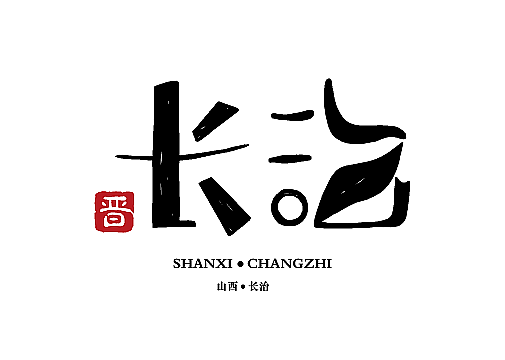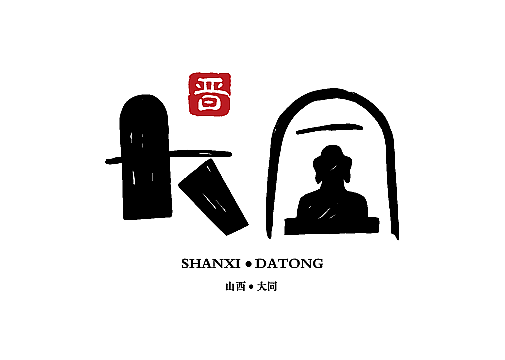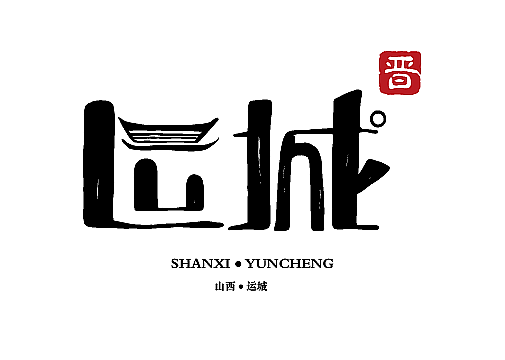
山西地名字体设计
山西是中华民族发祥地之一,有几千年的历史,具有“中国古代文化博物馆”之称。山西是一个典型的被黄土覆盖山比较多的高原,是具有许多古迹比较完整的古老遗址的旅游胜地。而我对山西11个市的市名进行字体设计,采用当地特色、旅游胜地及其建筑特征,对字体进行统一变形处理~
大同云冈石窟是世界文化遗产、国家5A级景区、首批全国重点文物保护单位。云冈石窟是世界闻名的石雕艺术宝库之一,是中国最大规模的石窟群~
阳泉-藏山风景是中华沧桑变迁的一幅重彩画卷,风景优美,历史氛围浓厚~
晋城,古称建兴、泽州、泽州府,自古为兵家必争之地,素有“河东屏翰、中原咽喉、三晋门户”的美誉~
我们或许对朔州不太熟悉,但是肯定听过走西口,而这个西口就是山西省朔州市杀虎口,而朔州最有名的是我国现存最高最完整的木塔——应县木塔~
长治,古称上党,上党梆子,山西省地方传统戏剧,国家级非物质文化遗产之一,所以我用脸谱的神韵与字体相结合,让整个字更像一个舞动水袖的花旦~
说到太原,不得不提的是太原晋祠,晋祠最为值得一看的便是雕塑、壁画、碑刻艺术,而它的建筑风格也令人耳目一新~
晋中相对于其他市而言,更像是一个古老建筑群体,其中比较有名的有榆次老城,乔家大院,平遥古城~
运城有很多景点,但被大家所熟知的当属鹳雀楼,鹳雀楼是现存最大的仿唐建筑,楼体壮观,结构奇巧,加之周围风景秀丽,唐宋之际文人学士登楼赏景留下许多不朽诗篇,以王之涣《登鹳雀楼》最富盛名~
忻州具有“旅游示范城市”之称,是修身养性的旅游胜地,而最为著名的是五台山~
临汾市历史悠久,是华夏民族的重要发祥地之一和黄河文明的摇篮,有“华夏第一都”之称~也是盛产汾酒的地方,是当地特色之一~
吕梁是革命老区,一部《吕梁英雄传》,是战争年代吕梁人民不畏牺牲、前赴后继的真实写照~